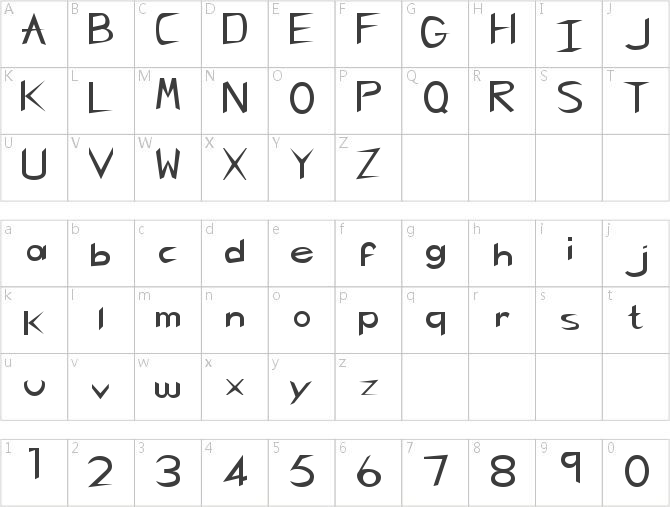
字体名称: Charlie
CharlieChan-Regular
CharlieChan-Regular介绍
CharlieChan-Regular字体字库是一款让人赏心悦目、百看不厌的英文字体,适合各类广告和产品包装设计应用,字体大小0.02MB,格式为ttf字体,上传用户是/zyj【GF】,作者/版权方为未知